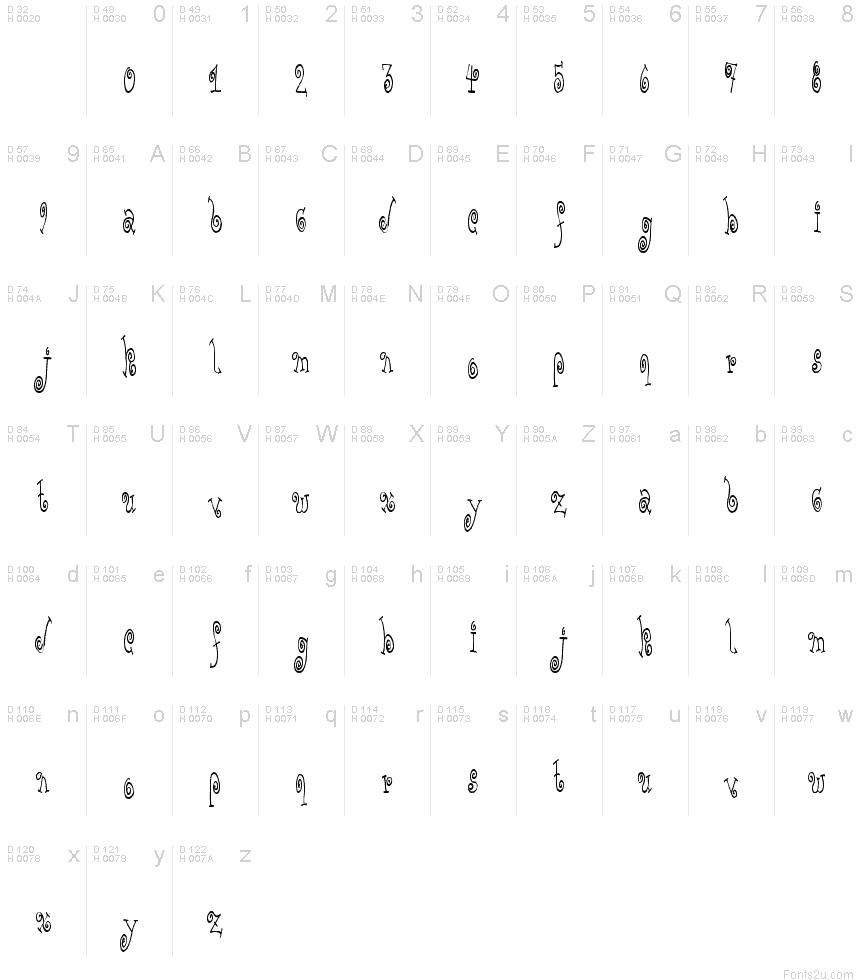
TPF Yolk Condensed
TPF Yolk Condensed(由 Samuel Marcius 设计)是一款免费的卷曲装饰字体,带有随性且充满童话色彩的氛围。字体高挑纤细,由纤细笔画构建而成,不断演化为大大的螺旋卷曲,让整款字体显得既俏皮又略带怪诞,甚至还有一丝戏剧感。
它非常适合海报标题、童书封面、咖啡馆招牌、活动传单以及需要手绘感而非平整精致外观的包装设计。作为一款免费字体,它在短标题、字母组合和标题卡中表现出色,那些重复的旋涡图案,即便只有寥寥几个字,也足以赋予页面独特的个性和张力。